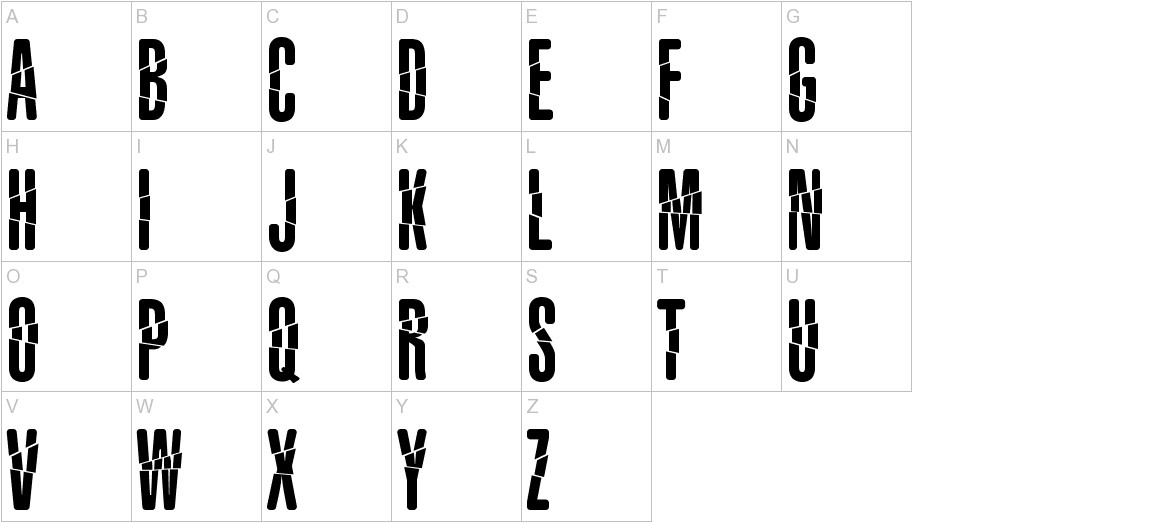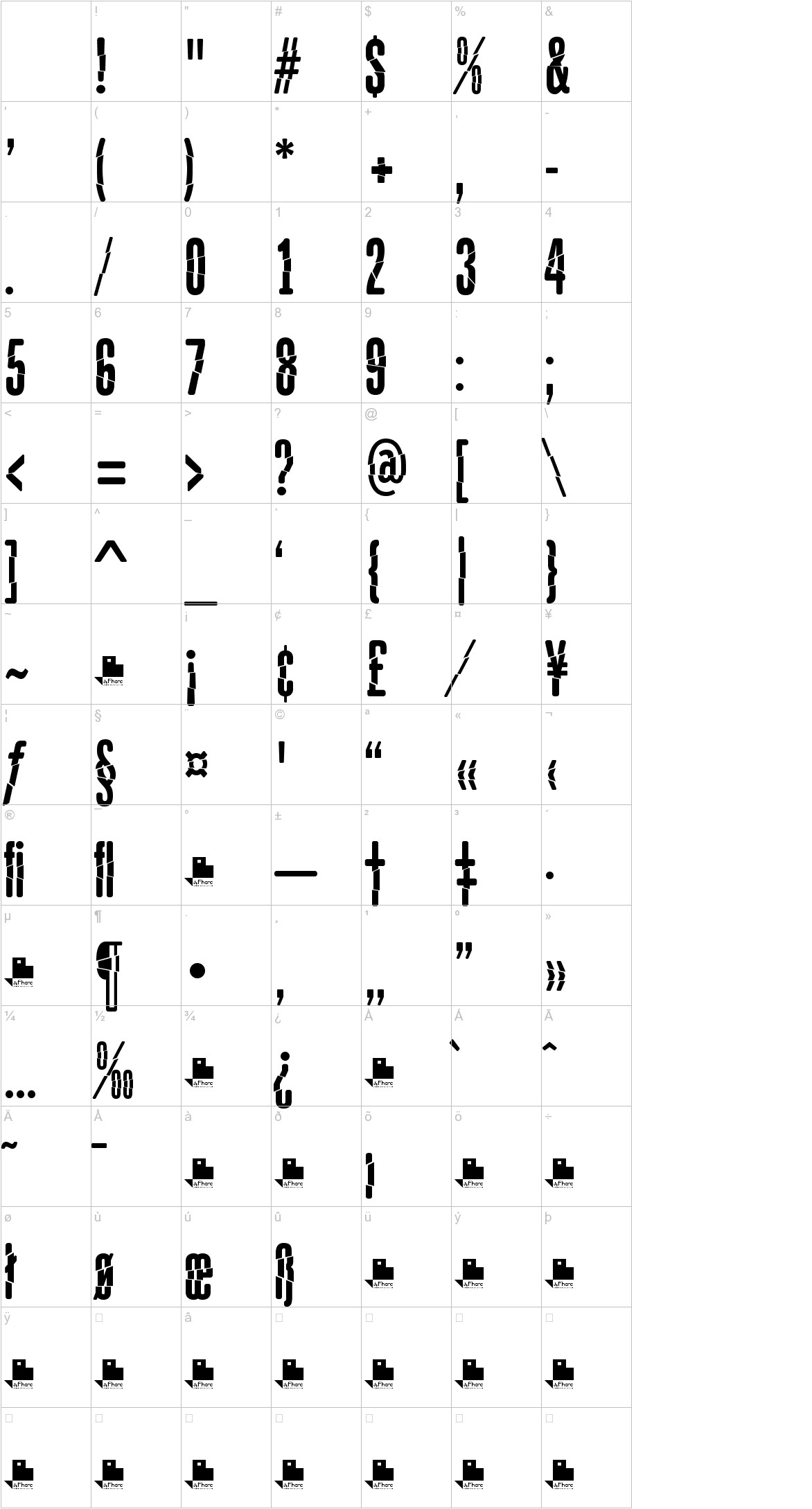
Babalusa Cut
Esta tipografía es un experimento de rajado y mutilación sobre mi anterior tipografía grotesca Yacarena Ultra Sans. Este ejercicio de corte aporta a la fuente una temporalidad estilística (moda) de la que no se sabe hasta cuando perdurará en el diseño gráfico, mientras tanto aprovéchala en composiciones de diseño de carteles, publicidad o para titulares en diseño editorial.
This typeface is an experiment in cracked and grotesque mutilation of my previous Yacarena Ultra Sans typeface. This exercise gives cutting power temporality stylistic (mode) of which is not known until they endure in graphic design, meanwhile kicking butt in compositions poster design, advertising or editorial design headlines.